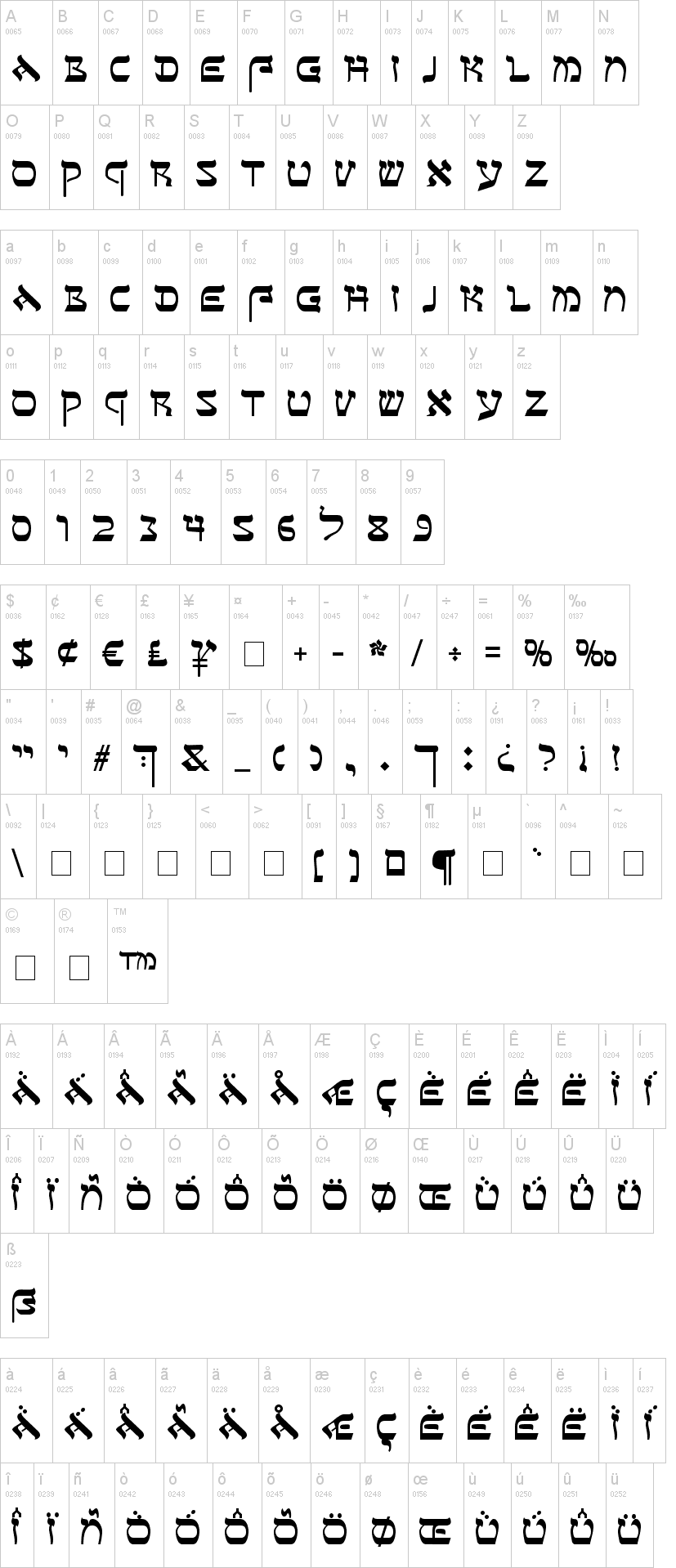
Sefer AH
Sefer AH 字体是一款古典的犹太文字体,由犹太字体设计师 Avraham Haber 创作。这款字体具有简洁、优雅的外观,其特点是笔画粗细均匀,拥有良好的可读性。它具有多种字体样式,可以用于创作书籍、文章等。此外,它还支持多种语言,如希伯来文、英文、俄文等。
Sefer AH是一款非常不错的手写艺术字体,具有很好的视觉感,适合于文化类的宣传设计、商业类品牌的广告和产品包装设计以及个性化文字排版等较多场景。
Sefer AH字符映射图